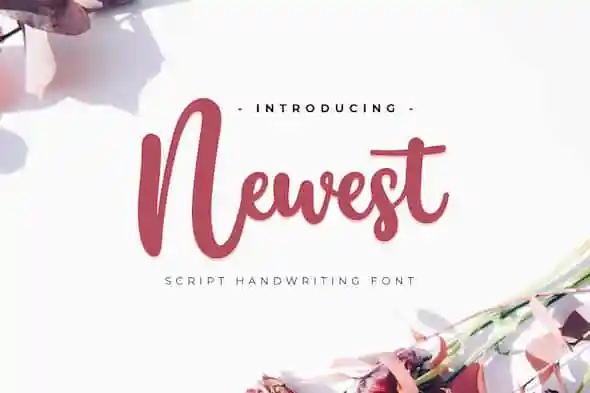
Newest Script Font – Download Grátis
Nova Font Script Moderna é uma fonte escrita a mão que captura as essências sutis e elegantes do estilo de escrevermos. Desenvolvida cuidadosamente para manter harmonia visual, esta fonte moderna mantém um charme único com suas belas curvas em cada letra. Tanto designers profissionais quanto amadores apreciarão a maneira como a Nova Font Script moderna adiciona uma qualidade única e criativa ao seu trabalho. Foi pensada para oferecer um toque sofisticado sem deixar de lado o charme elegante que faz com que cada palavra seja única e envolvente. O resultado é uma fonte escrita a mão que não apenas enriquece sua designação, mas também torna-a mais autêntica e personalizada.